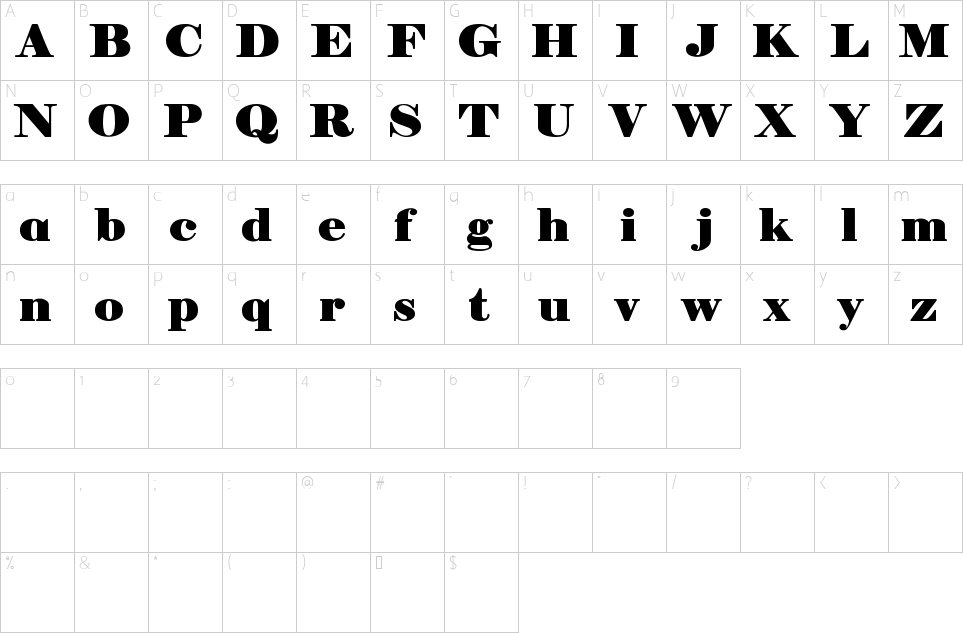
Manuell é uma fonte gráfica que oferece uma gama de caracteres para textos legíveis e elegantes. Desenvolvida pelo designer EvasUniqueFonts, ela se destaca por seu design limpo e moderno, ideal para aplicativos de design gráfico e editoriais de blog. Com seu design personalizado e sua ampla gama de uso, Manuell foi baixada mais de 10.000 vezes, demonstrando sua popularidade entre designers e criadores de conteúdo. Seja para criar um site profissional, uma publicação online ou até mesmo um design de gráficos de arte, Manuell é uma excelente opção para aqueles que buscam um visual agradável e funcional. Descubra por si mesmo, o impacto de Manuell em seu próximo projeto.